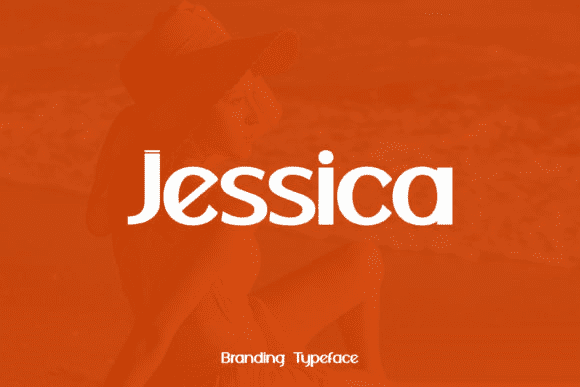
Jessica - это чистый и современный шрифт.
Добавьте этот минималистский шрифт в стиле техно к своим веб-дизайнам, логотипам или всему, что требует умного и холодного штриха.